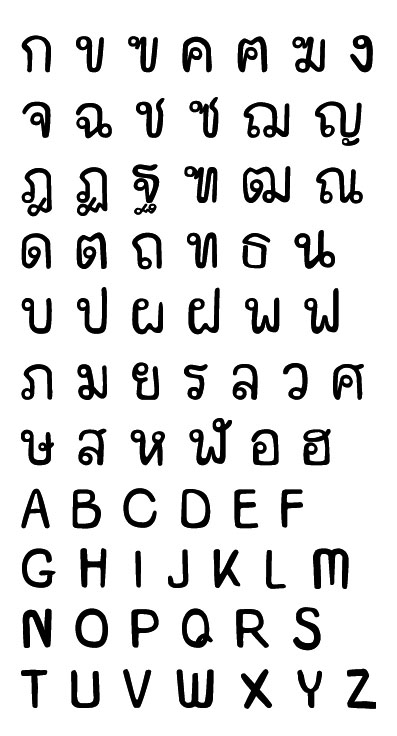
ฟอนท์ youth ครับ
ทำไว้นานแล้วครับ ไว้ใช้เอง
เคยมาแปะไว้แล้วครั้งนึง ช่วงประกาศผลประกวดฟอนท์รอบแรก [ผมตกรอบแรก 555 :03:]
แต่คราวที่แล้วอวดไม่ครบอักษร...
เชิญติชมกันตามอัธยาศัยครับ
โหยยย   :25: :25: :25:
น่าร๊าากกกก
สวย :25:
เจาะหัวแจ๋วไปเลย
เหวอ.... โดนแย่งลูกค้าแล้ว ...... สวยครับ
สวย สะอาดตา  :12:
ฑ ท ผมว่าน่าจะกว้างกว่านี้หน่อยก็ดีนะครับ เผื่อตัวเล็กเดี๋ยวมันทึบ . :45: